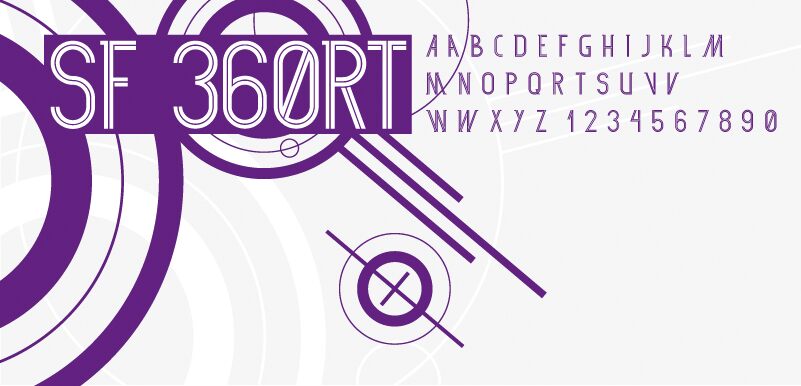
SF 360RT von Jens Nink ist eine kostenlose, konturierte Retro-Display-Schrift, die aus klaren, doppelt geführten Strichen und weiten geometrischen Kurven aufgebaut ist. Ihre hohen, schmalen Formen erinnern an technisches Zeichnen und Beschilderungen des späten 20. Jahrhunderts, wobei eckige Verbindungen und offene Linien im Inneren dem Schriftbild ein präzises, konstruiertes Erscheinungsbild verleihen.
Sie überzeugt besonders im Technologie-Branding, wo die lineare Konstruktion Instrumente, Schaltkreise oder kalibrierte Anzeigen evozieren kann. Derselbe maßvolle Stil passt zu Science-Fiction-Titelkarten und Plakaten für elektronische Musik und verleiht Produktverpackungen eine kühle, industrielle Note. Diese parallelen Konturen können zudem Diagrammlinien oder Interface-Grafiken aufgreifen, wodurch die Schrift zu einem Teil eines technischen visuellen Themas wird, statt nur eine Beschriftung zu sein.